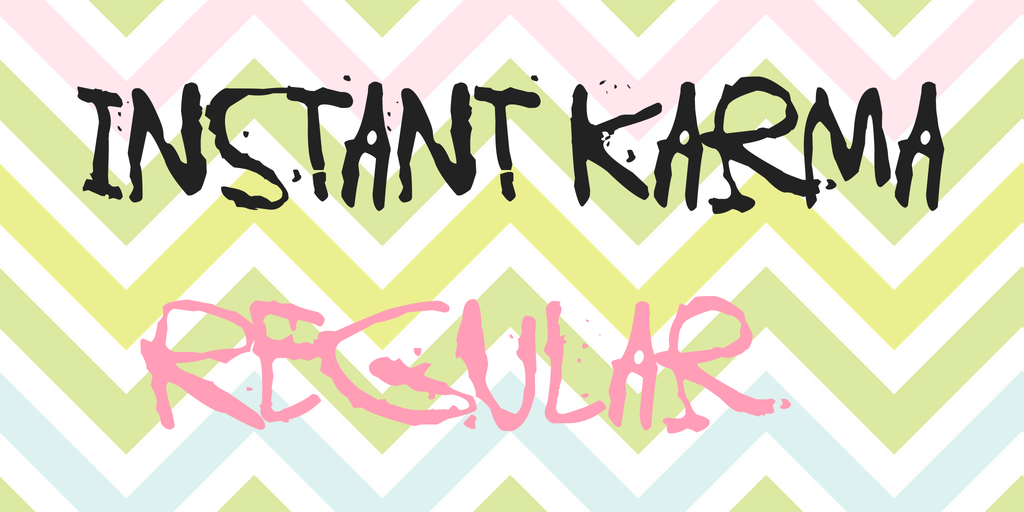
Instant Karma Font
Aqui está uma descrição natural para a página de download do ‘Instant Karma Font’, mantendo-se fiel ao conteúdo original mas com um tom mais informativo e convidativo: Aprenda sobre a fonte escrita à mão Instant Karma, criada por Juha Korhonen. Este é um tiro na corda bem-sucedido para designers de gráficos que procuram uma caligrafia elegante e fluida para seus projetos pessoais. A fonte foi liberada gratuitamente para uso pessoal. Para usar Instant Karma em projetos comerciais, você pode comprar a licença comercial por meio de um pagamento simples com o método de pagamento seguro PayPal. Basta enviar 15€ (aproximadamente $20) e lembre-se de enviar uma mensagem depois da confirmação do pagamento, para que você possa continuar utilizando a fonte. Além disso, há um botão “Doar” disponível próximo ao botão de download. Se desejar, pode colaborar com Juha Korhonen fazendo regularmente seu “doação”, o que é sempre bem-vindo e estimado por ele. Se você está procurando uma fonte escrita à mão única para seus projetos gráficos pessoais, Instant Karma é a escolha perfeita. Aproveite esse tiro na corda, experimente essa fonte e venha explorar mais designs únicos de fontes de Hamilton em nosso site!